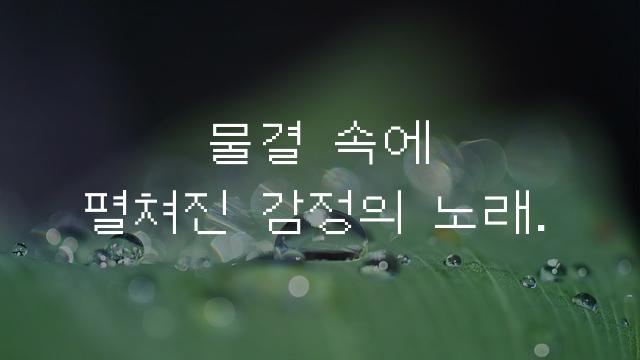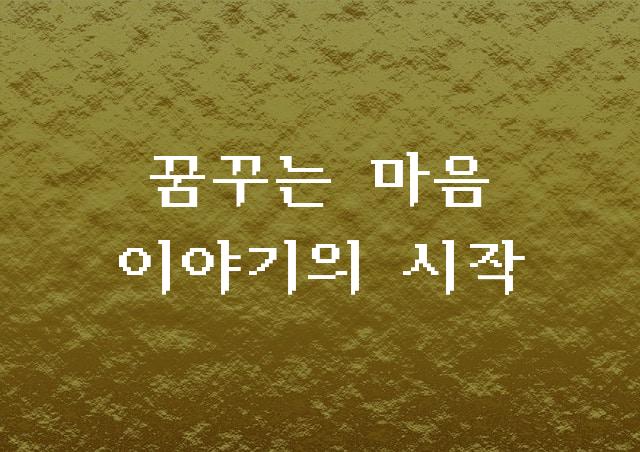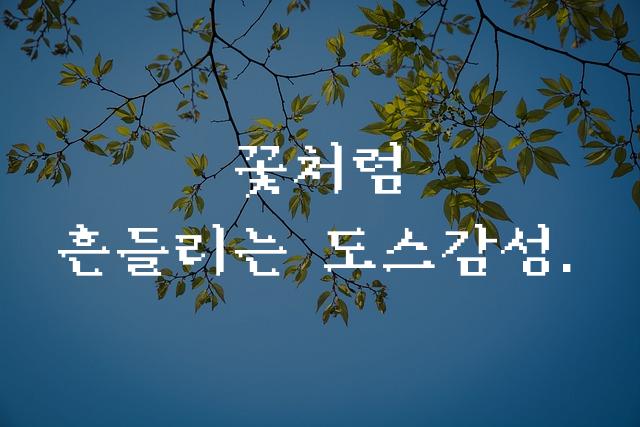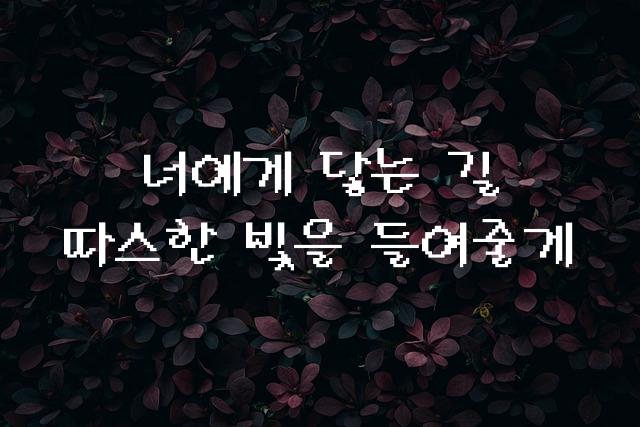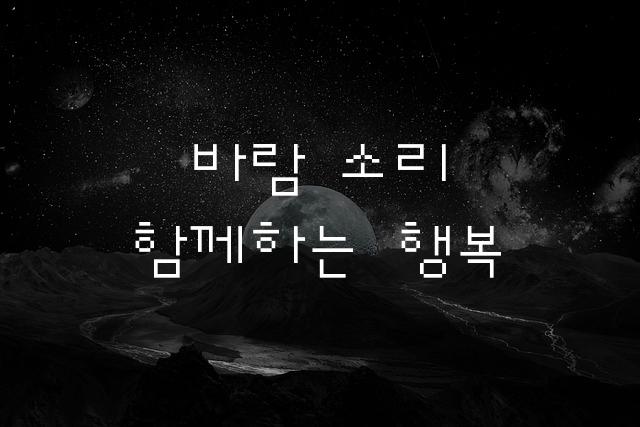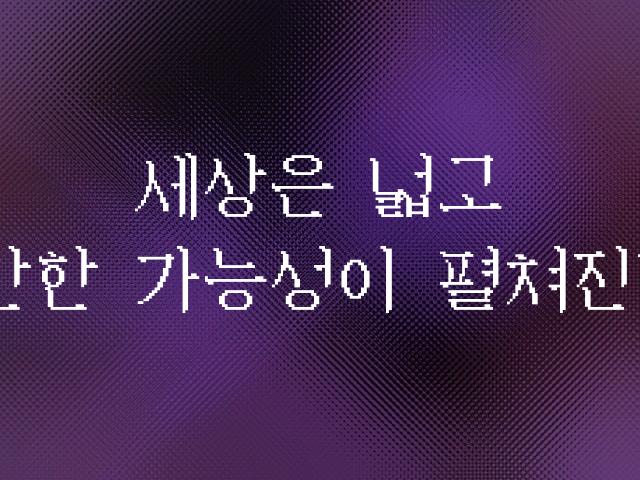
삼국지3글꼴은 장식적인 바탕과 픽셀 도트 스타일을 결합하여 독특한 감성을 자아내는 폰트입니다. 고전적인 느낌과 현대적인 디자인이 조화를 이루며, 디지털과 아날로그의 경계를 허물어냅니다.
삼국지3글꼴은(는)
바탕 스타일, 픽셀/코딩, 레트로, 장식 스타일, 감성적인, 게임 느낌, 별모양/패턴 계열의 생김새를 가지고 있으며
포스터, 광고 캠페인, 출판물 제목 등에서 자주 활용되며, 효과적인 메시지 전달에 적합합니다.
이 폰트는 문화/예술, 엔터테인먼트, 이벤트/웨딩 분야에 잘 어울리며,
강렬한, 예술적인, 클래식한 느낌을 담고 있는 것이 특징입니다.